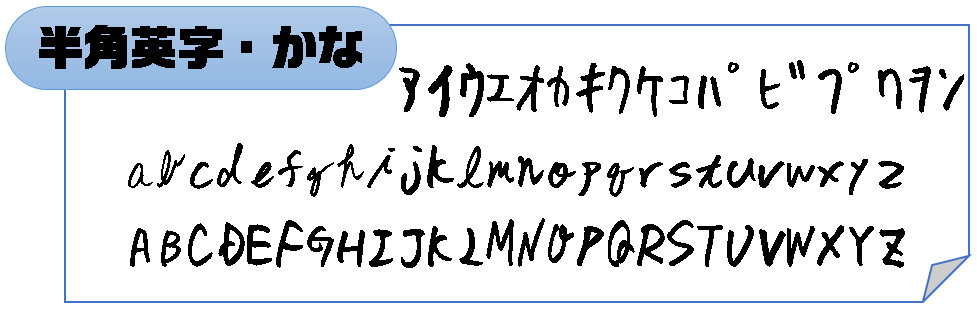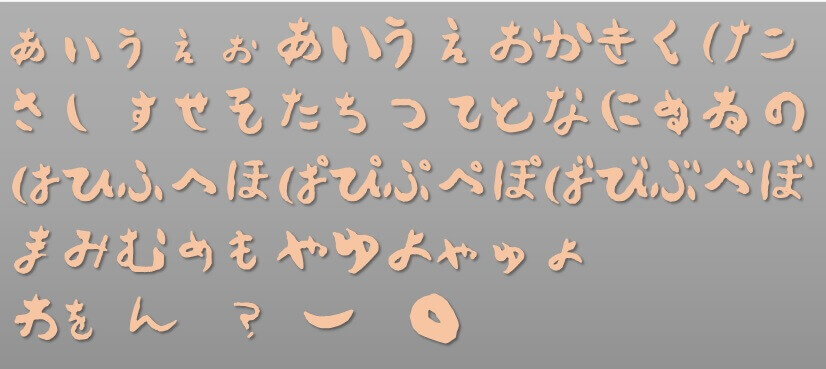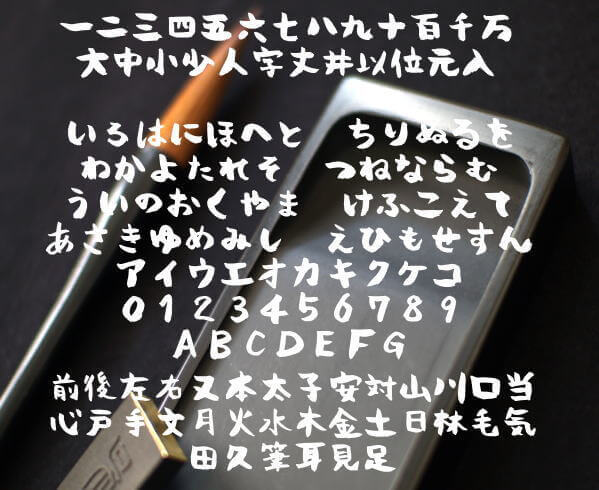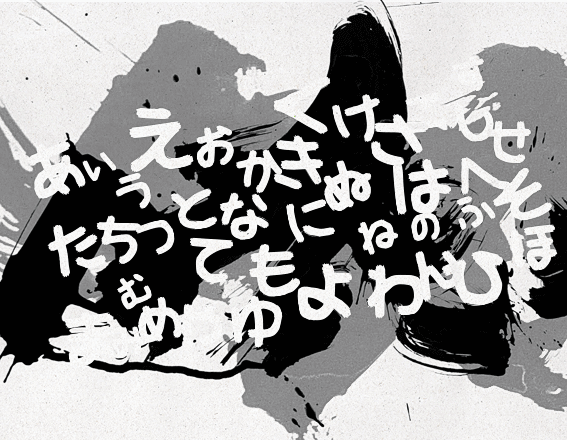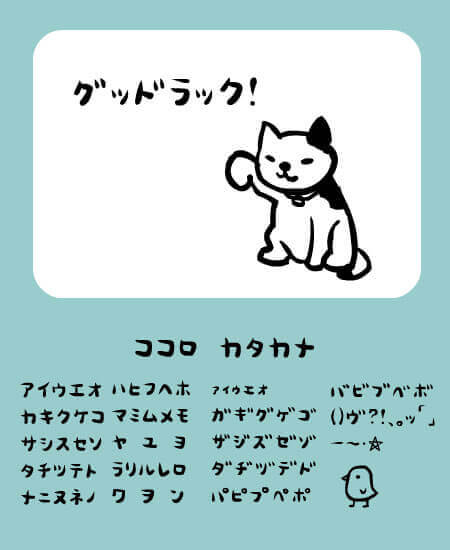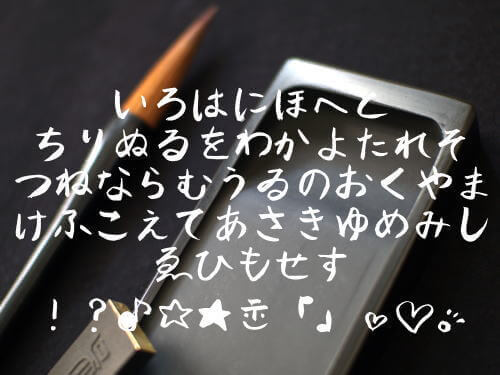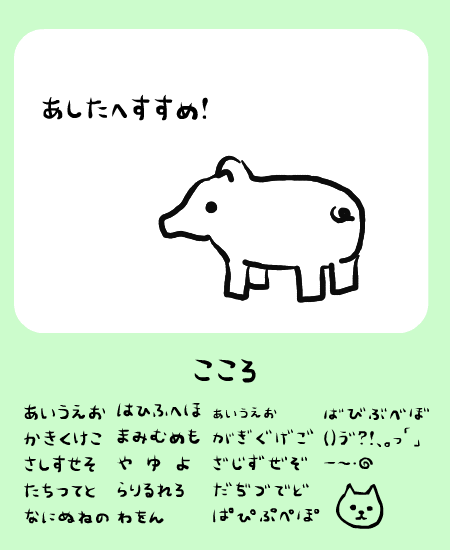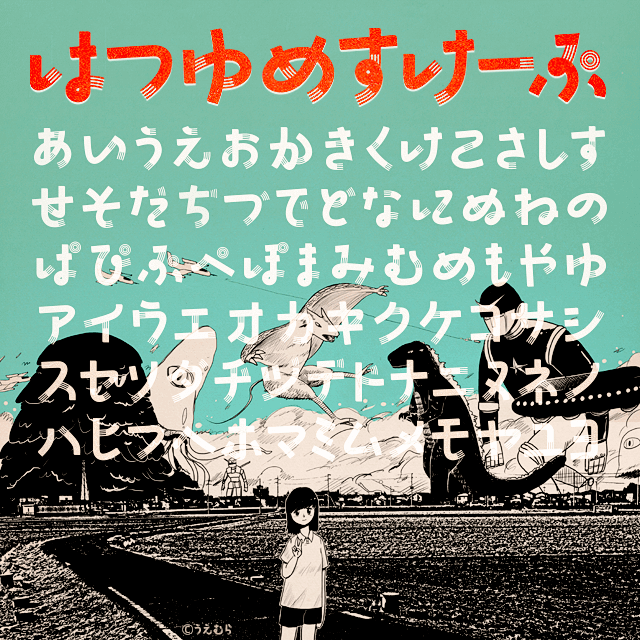
無料でダウンロード!ポップな筆文字フォント21選
筆文字の中でも堅苦しくなく、割とポップな仕上がりになっている無料でダウンロード可能なフォントを集めました。公式的な表彰状、のし紙などの贈答品には不向きですが、チラシ・POP・ポスターなど、ちょっと崩したデザインに活用できそうです。各ライセンスをご確認の上ご利用ください。
g_丸かな体
コミックのセリフやモノローグに使用する事を目的として作成されたフォント。ロゴ、印章、年賀状の文字等にピッタリ。漢字は未収録。
KFひま字ふで
ぷっくりとした筆文字のようなフォント。子供向けのデザインに合いそうな文字。
アボカド
毛筆風日本語フォント。手書きのメニューなどに使えそうな文字。
おくりびとフォント
映画「おくりびと」で使用されているようなフォント。収録文字はひらがなのみ。
かきぞめフォント
筆で書いたラフな手書き風フォント。 商用利用する場合、製品版の購入が必要。
こころ
手書き文字フォント。素朴な雰囲気のデザインに合う文字。
ココロカタカナ
上記で紹介した「こころ」フォントのカタカナバージョン。
こころフォント
手書きフォント。上記で紹介した「こころ」の2バイトフォント。ひらがな、カタカナに加え、アルファベット、数字、記号も追加。
さなフォン帯
カリグラフィペンで書いたような、飾り文字。挨拶状やお祝い事のカードなどの利用にどうぞ。
じゃぽねすく
筆文字風のフォント。半紙にしみた感じがでていそうな文字。
タロコフォント
筆ペンで書いたような居酒屋チックなフォント。漢字は教育漢字を収録。
とねり
垂らした墨を指で伸ばして書いたようなフォント。ひらがな、カタカナを収録。
はつゆめすけーぷ
筆文字を意識しつつも現代的なデザインが楽しいフォント。和風のデザインだけど、手書きや筆文字では昔っぽすぎて、もっとポップな文字が欲しいという時に役立つ文字。商用利用する場合、製品版の購入が必要。
フォントコンバーターひらカナ
尋スタジオが提供しているフリーフォント「ひらがな(ZiF Ahi)」「カタカナ(ZiF Aka)」の2種類が収録。
みきゆフォント毛筆体
素材屋405番地から公開されている「みきゆフォント」の毛筆体バージョン。年賀状などの利用にピッタリ。
りいてがき筆
手書きの筆文字フォント。かわいい雰囲気が出ている文字。漢字は、JIS第1水準および第2水準を収録。
渦筆
筆ペンで書かれたフォント。和紙に合いそうな雰囲気なので和食のお店のお品書きにオススメ。
漆黒フォント